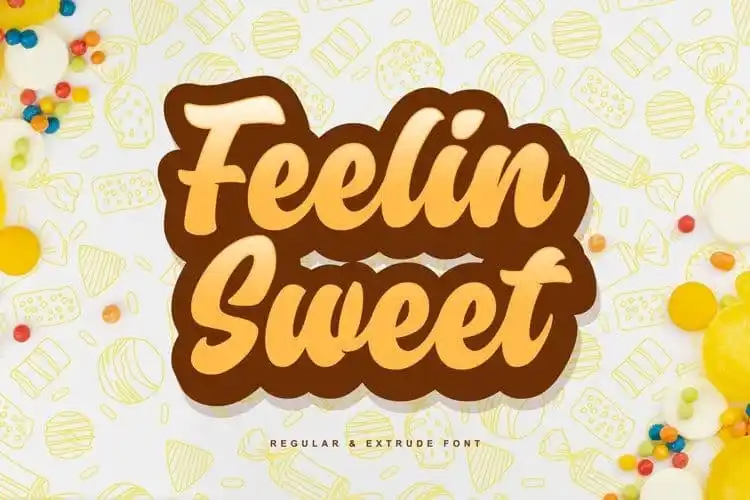
Feelin Sweet Script Font – Download Grátis
A ‘Feelin Sweet Script Font’ é uma escolha excepcional para quem busca uma fonte com traços elegantes e um toque vintage. Esta fontes tem curvas suaves, dando-lhe um aspecto atraente e fluido. Ao mesmo tempo, a sua aparência deslizante proporciona um brilho fresco e jovial, ideal para projetos de gráficos modernos ou retro. As duas opções disponíveis – Regular e Extrude – permitem que você personalize o projeto de acordo com seu gosto pessoal, adicionando uma dimensão única e agradável ao texto. Esta fonte traz consigo um toque autêntico e sofisticado, tornando-a perfeita para aplicar em variados projetos gráficos – seja um site moderno ou um flyer vintage. Não hesite em experimentá-la na sua próxima criação de design.